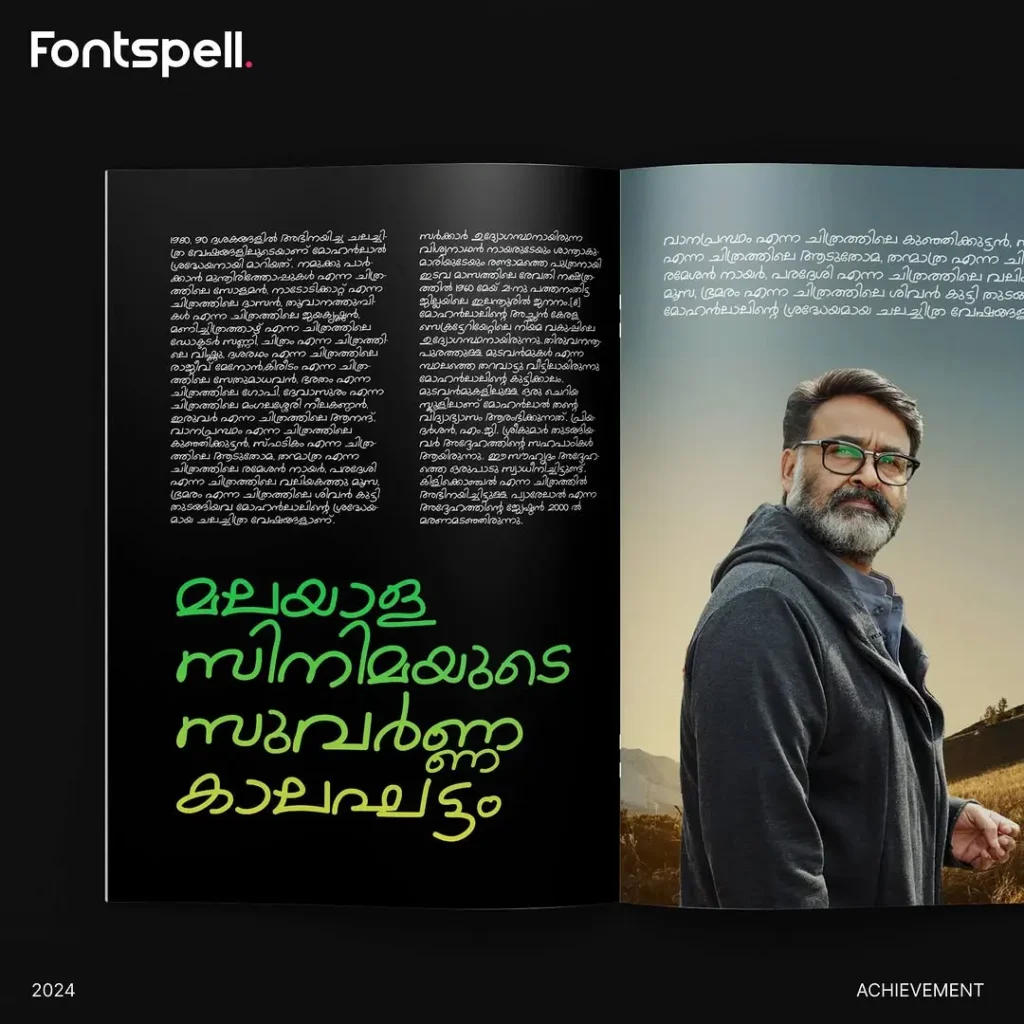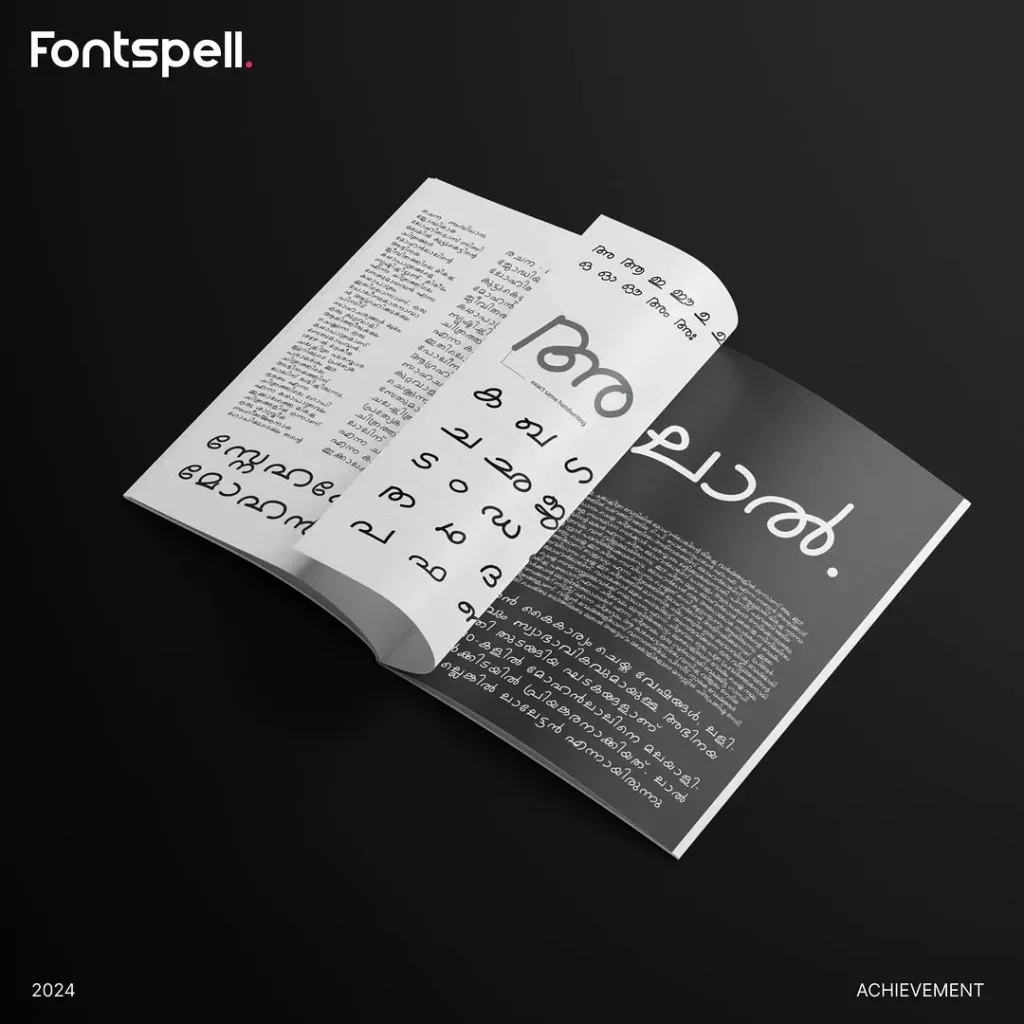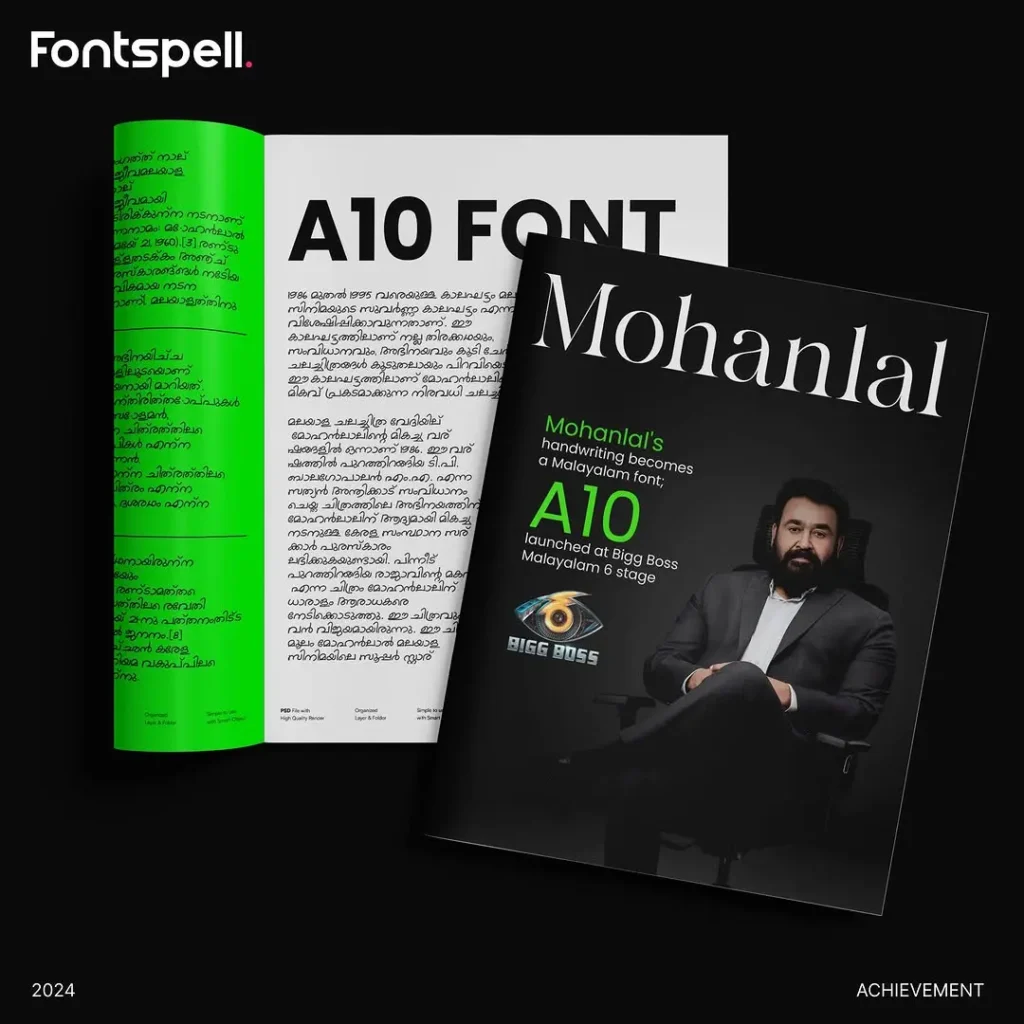
മോഹൻലാലിന്റെ ജന്മദിനം – ‘A10’ ഫോണ്ടിന്റെ പ്രകാശനം
നമ്മുടെ ഏവരുടെയും പ്രിയപ്പെട്ട ലാലേട്ടന്റെ ജന്മദിനത്തിൽ, അദ്ദേഹത്തിന്റെ കൈയെഴുത്തിന്റെ പ്രതിരൂപമായ ‘A10’ ഫോണ്ട് ഡിജിറ്റൽ ഫോണ്റ്റായി പുറത്തിറക്കിയിരിക്കുന്നു. ഒരു പ്രധാന പ്രത്യേകത എന്തെന്നാൽ, ഈ ഫോണ്ട് എല്ലാവർക്കും സൗജന്യമായി ലഭ്യമായിരിക്കും. ഒരു നടന്റെ കൈയെഴുത്ത് ആദ്യമായാണ് ഡിജിറ്റൽ ഫോണ്ടിലേക്ക് മാറ്റപ്പെടുന്നത്.
ലാലേട്ടന്റെ ഈ കൈയക്ഷര ഫോണ്ട് ക്രീയേറ്റ് ചെയ്തിരിക്കുന്നത്: Fontspell
A10 ഫോണ്ട് എന്താണ്?
‘A10’ എന്നത് ഒരു ഡിജിറ്റൽ ഫോണ്ട് ആണ്, മോഹൻലാലിന്റെ കൈയെഴുത്തിന്റെ മുഴുവൻ സവിശേഷതകളും ഉൾക്കൊണ്ടാണ് ഇത് രൂപകൽപ്പന ചെയ്തിരിക്കുന്നത്. ഏഷ്യാനെറ്റ് മോഹൻലാലിന്റെ ജന്മദിനാഘോഷ വേളയിൽ ഇത് പ്രഖ്യാപിച്ചിരുന്നു.
മോഹൻലാൽ – ദി_complete_actor
മോഹൻലാൽ വിശ്വനാഥൻ, ഇന്ത്യയുടെ പ്രശസ്ത നടനും, നിർമ്മാതാവും, സംവിധായകനും, ഗായകനും, സിനിമാ വിതരണക്കാരനും, ടെലിവിഷൻ അവതാരകനുമായ അദ്ദേഹം 40 വർഷമായി ഈ മേഖലയിൽ ഉള്ളാരാളാണ്. ദി കംപ്ലീറ്റാക്ടർ എന്ന വിശേഷണത്തോടെ, അദ്ദേഹം പ്രധാനമായും മലയാള സിനിമയിൽ പ്രശസ്തനായിട്ടുള്ളതും, തമിഴ്, ഹിന്ദി, തെലുങ്ക്, കന്നഡ ഭാഷകളിലും അഭിനയിച്ചിട്ടുള്ളതുമാണ്.
A10Font is a Malayalam font crafted specifically for impactful titles. This elegant typeface brings a touch of sophistication to your designs, making headlines truly stand out.